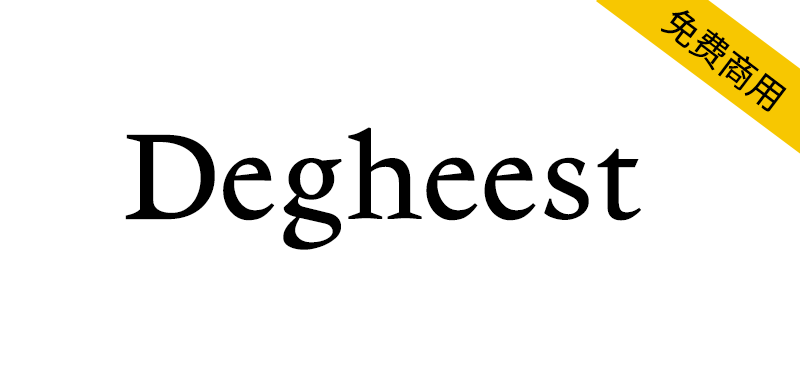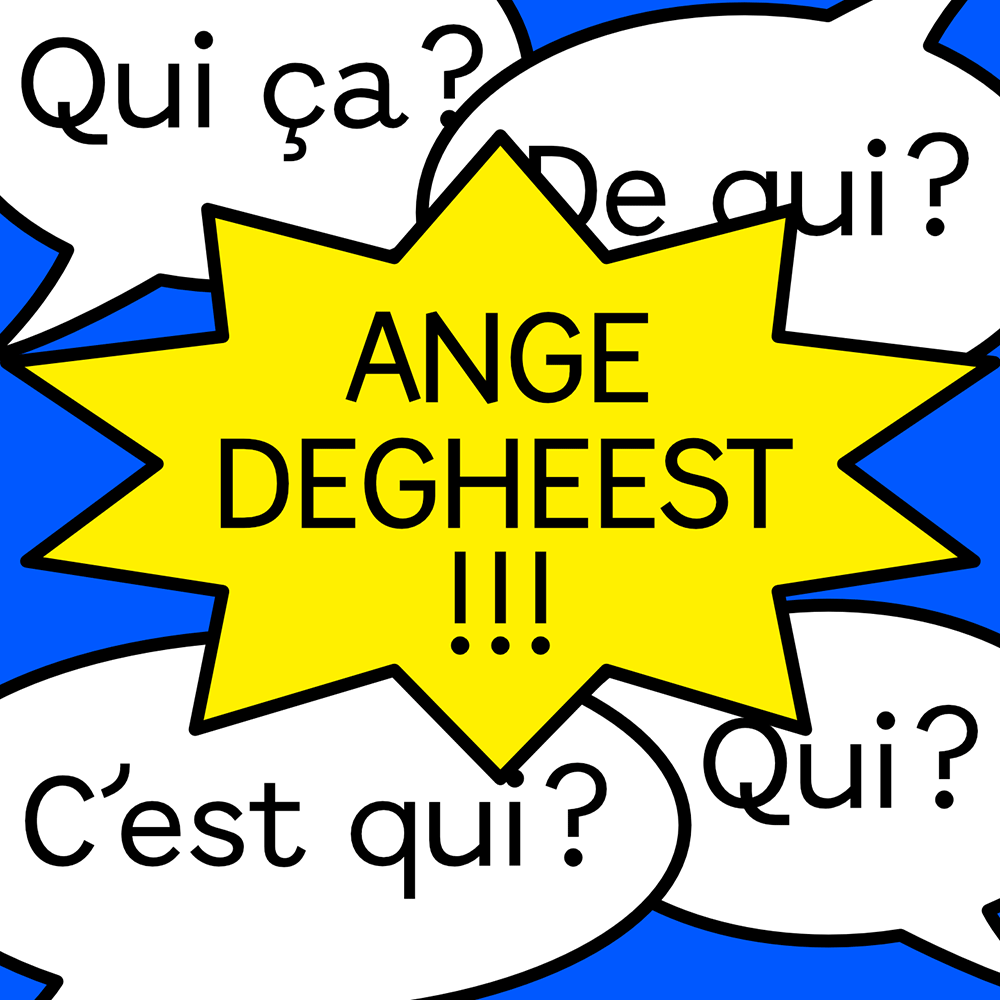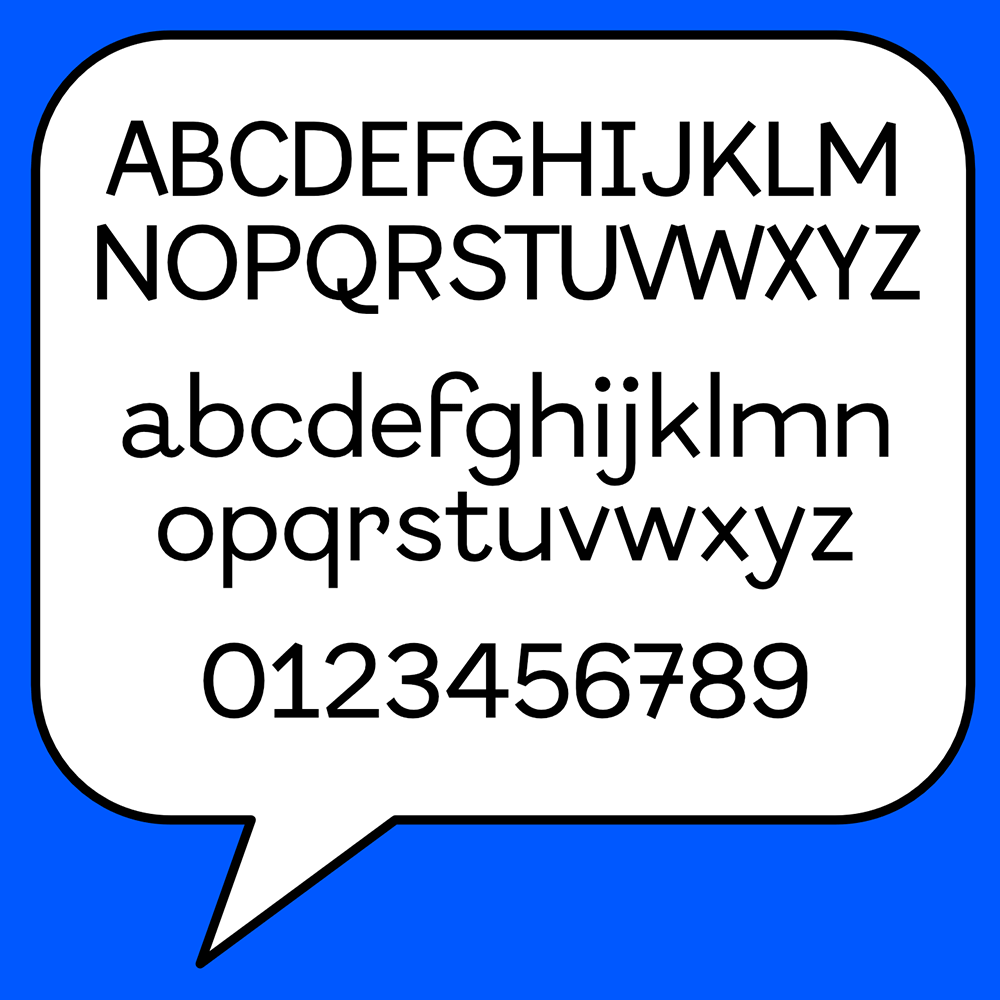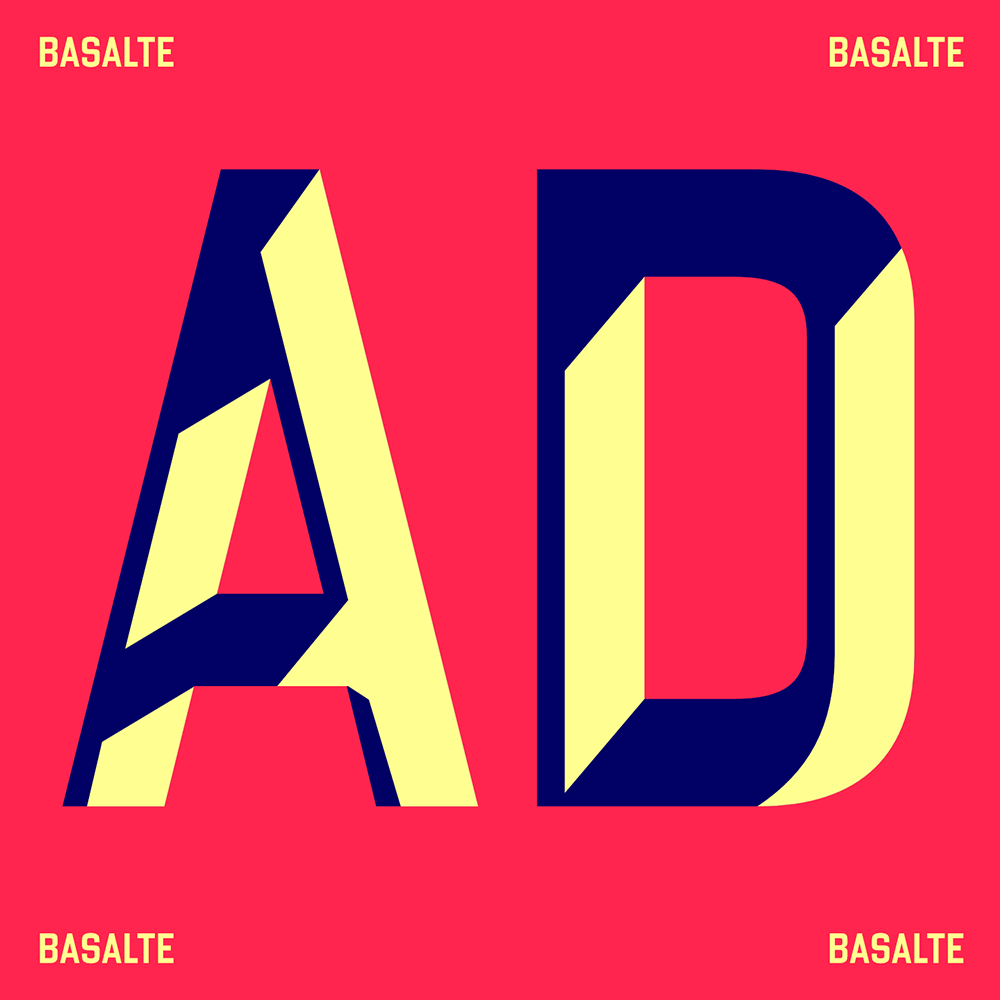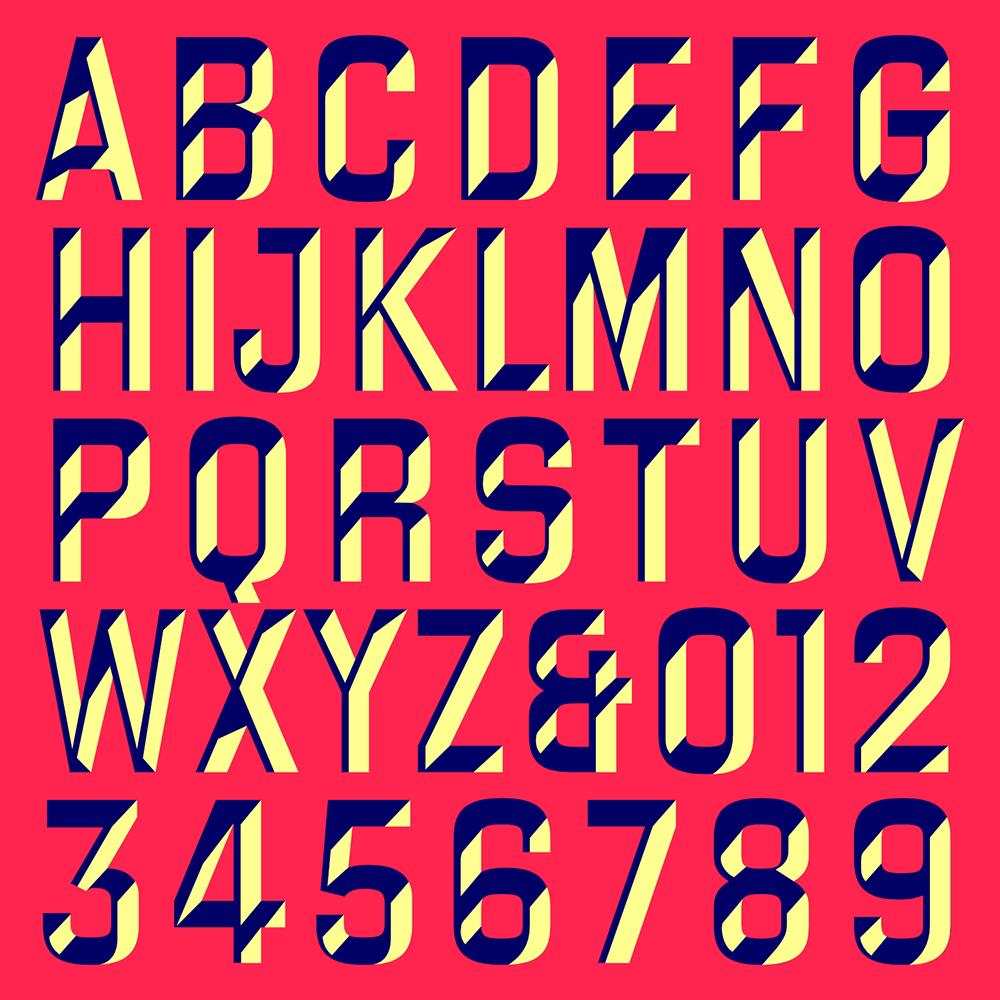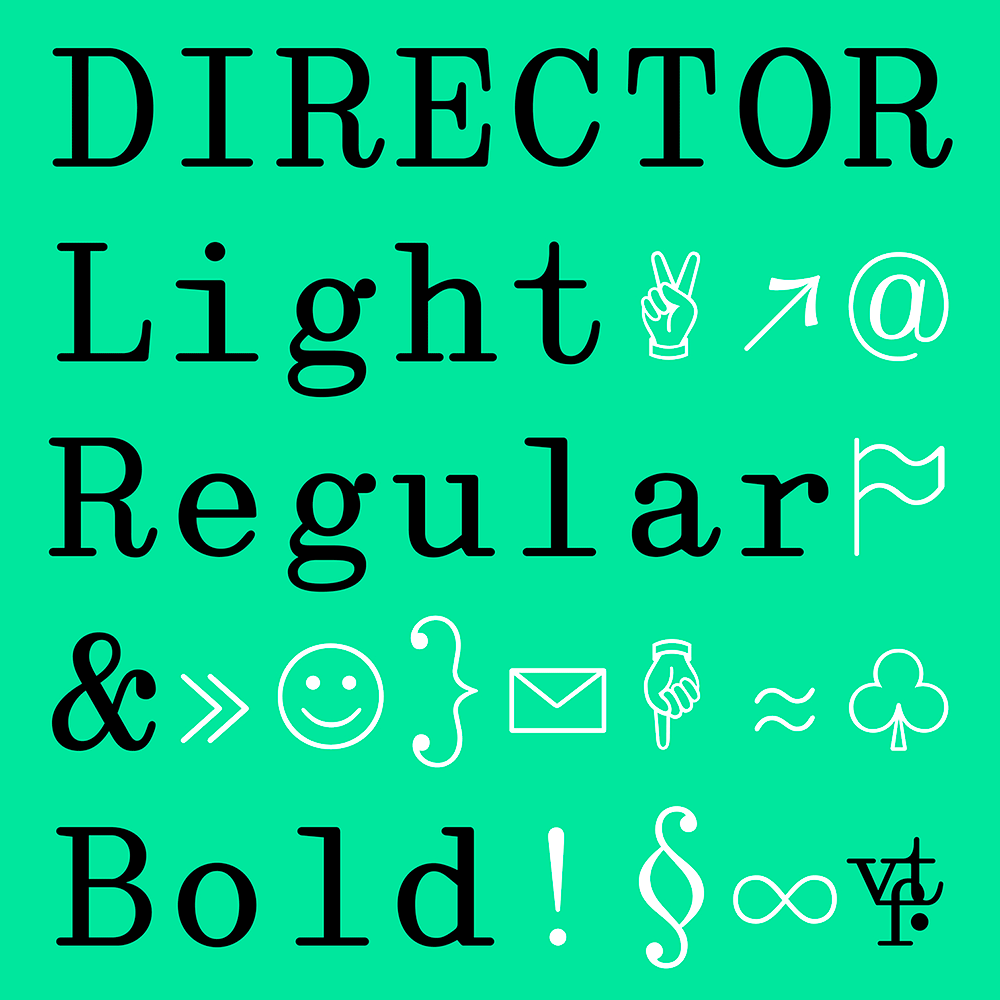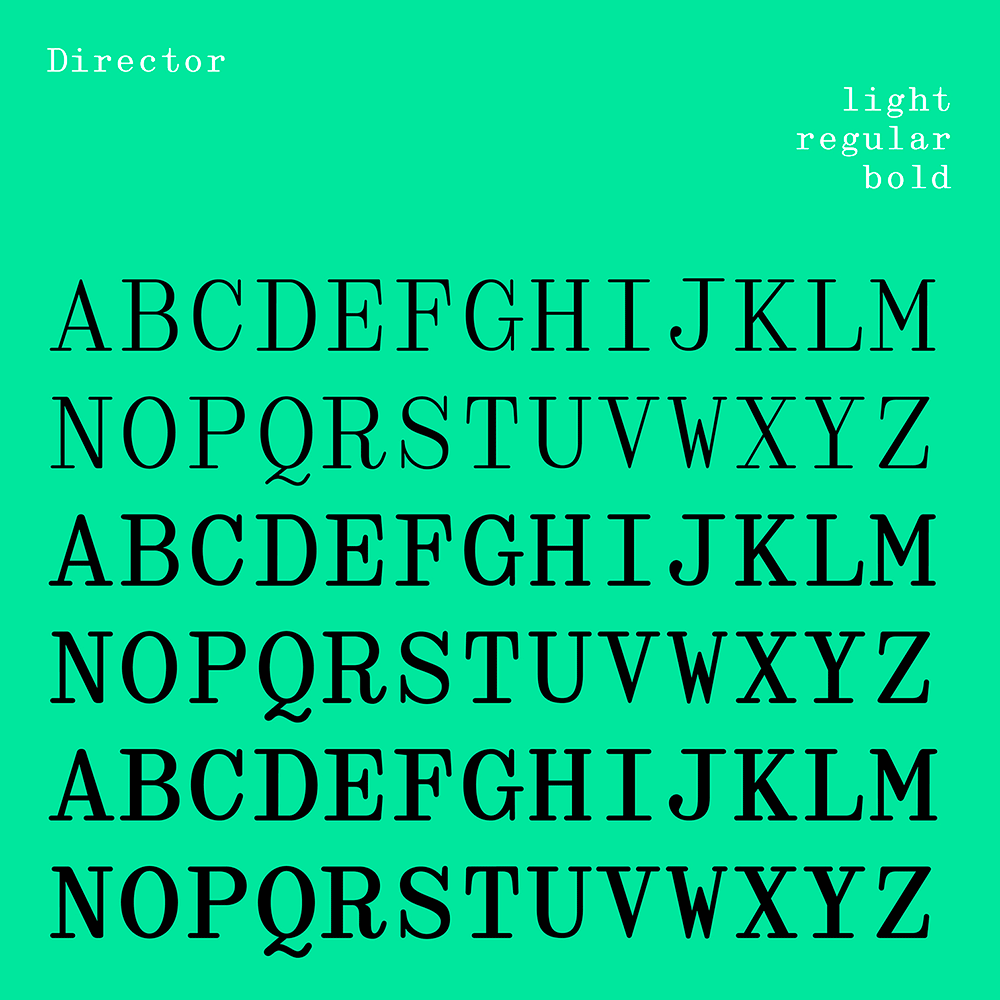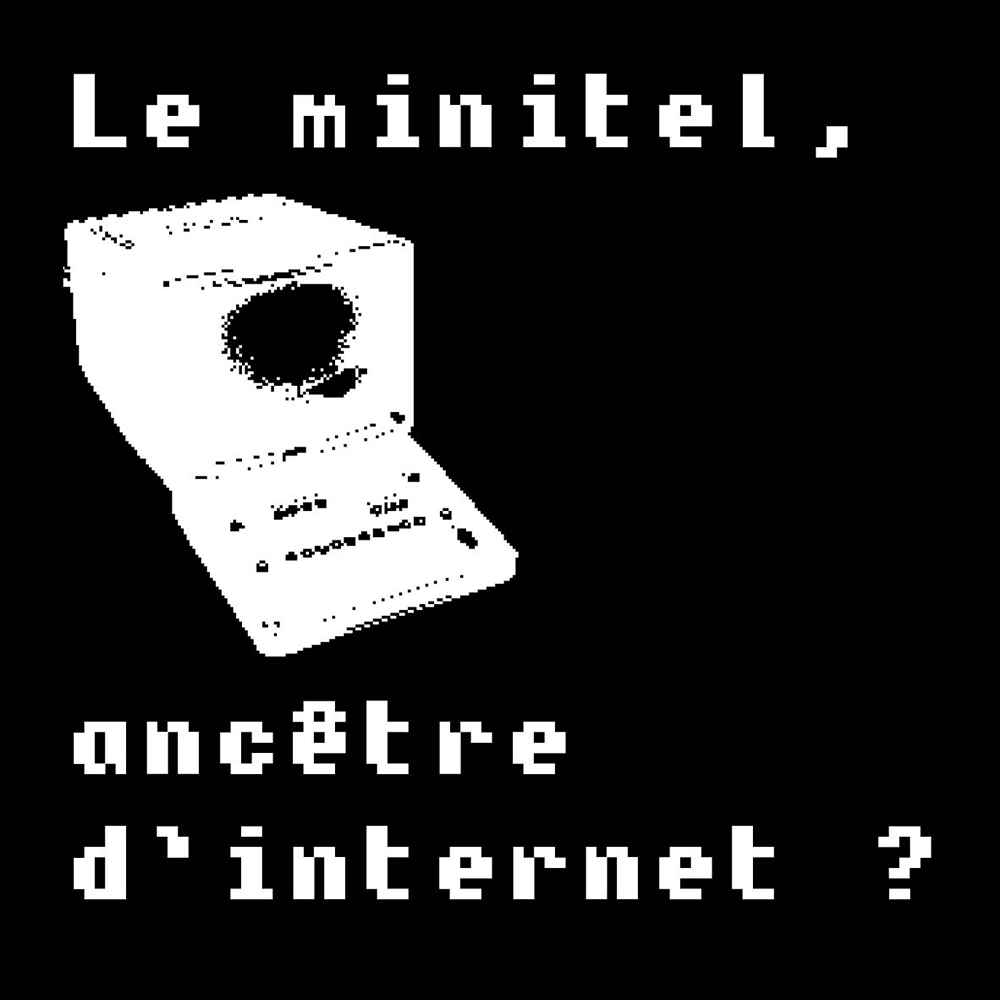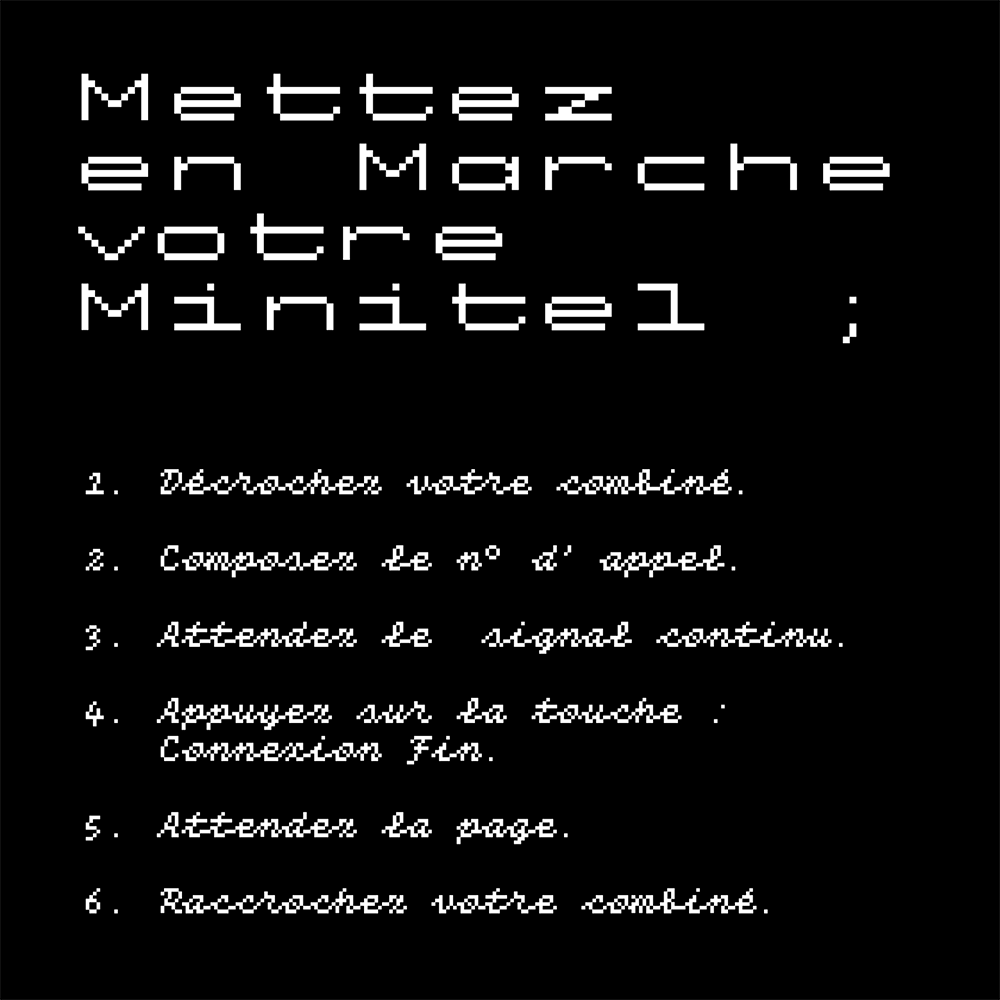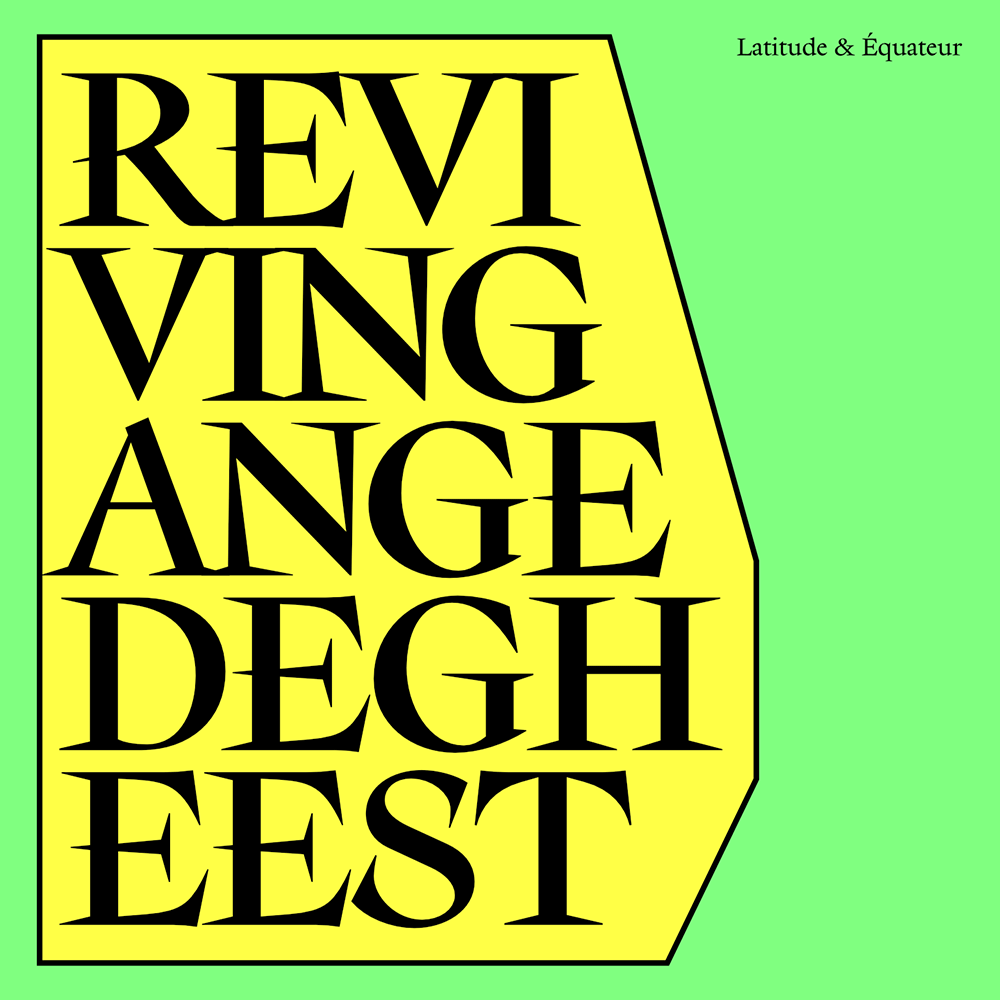
在雷恩美术学院发现Ange Degheest的档案后,我们决定举办一场展览,试图最终给予这位设计师她应得的充分认可。在这次展览中,参观者了解了Degheest的生活故事和职业成就,并发现了许多以前从未向公众展示过的原始档案文件。除了这项历史研究,我们还恢复了Ange Degheest的一些最引人注目的字体和刻字作品,这些作品现在可以在Velvetyne Type Foundry的网站上以开源许可的数字格式提供。
复活意味着:复活、重新激活、更新;在很多方面,我们的工作都是一种复活。我们确实不得不通过翻阅Ange Degheest的档案,挖掘一个经历了许多时代和地点的女人的故事,来重新唤起对她的记忆。只有当我们很好地了解了她的生活故事,我们才能恢复她的字体。复兴她的设计并免费广泛分发,是我们纪念Ange Degheest并在21世纪赋予其新生命的方式。
Deheest是Ange Degheest、Eugénie Bidaut、Oriane Charvieux、Mandy Elbé、Luna Delabre、Camille Depalle、Justine Herbel、May Jolivet和Benjamin Gomez在雷恩EESAB印刷工作室创作的一个项目。
After discovering Ange Degheest’s archives at the Rennes School of Fine Arts, we decided to put together an exhibition that attempted to finally give the designer the full recognition she deserves. In this exhibition, visitors learnt about Degheest’s life story and professional achievements, and discovered many original archival documents that had never previously been presented to the public. In addition to this historical research, we revived some of Ange Degheest’s most remarkable typefaces and lettering work, which are now available in digital format under an Open Source license on Velvetyne Type Foundry’s website.
To revive means: to resurrect, to reactivate, to renew; and in many ways our work consisted in a kind of resurrection. We had indeed to reactivate the memory of Ange Degheest by diving in her archives, by exhuming the story of a woman who lived through many ages and locations. Only once we had acquired a good grasp of her life story, were we able to revive her typefaces. Reviving her designs and distributing them widely, free of charge, is our way to honour Ange Degheest’s memory and to give them a new life in the 21st century.
Deheest is a project by Ange Degheest, Eugénie Bidaut, Oriane Charvieux, Mandy Elbé, Luna Delabre, Camille Depalle, Justine Herbel, May Jolivet and Benjamin Gomez, created in Atelier de création typographique from EESAB Rennes.